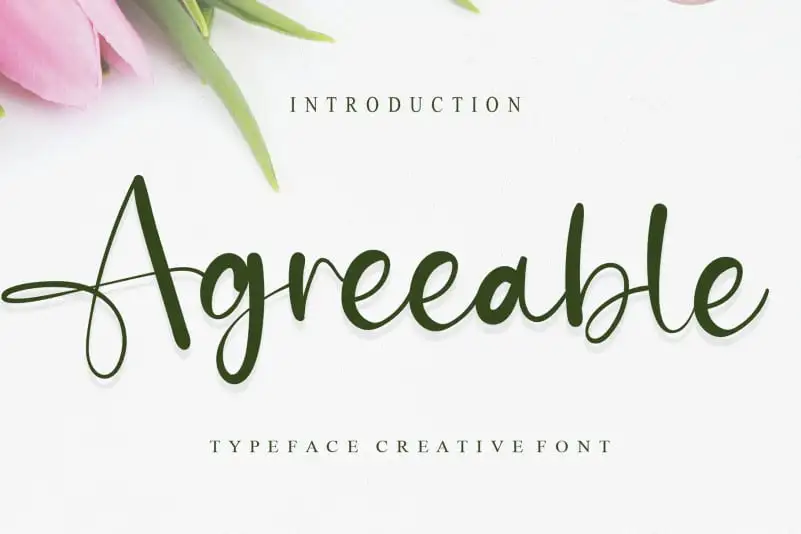
Agreeable Calligraphy Font – Download Grátis
Descubra uma nova experiência com a Fonte Script ‘Agreeable Calligraphy’. Inspirada no universo natural brasileiro vibrante e diversificado, esta fonte traz uma sensação de caligrafia delicada e sofisticada. Seu designer, andikastudio, criou este recurso especial para oferecer aos seus usuários um produto excepcionalmente original que reflete a riqueza cultural do Brasil. Através deste script fonte, você pode capturar o jeito quase mágico como as folhas de árvores dançam ao vento em meio à paisagem verde e acolhedora da nossa Amazônia. Ou, se preferir, a caligrafia mais suave do sertão nordestino, onde o ar é densoado pela força das tempestades que chegam das águas do Atlântico. Essa fonte não apenas oferece uma maneira única de expressar palavras e ideias, mas também oferece um convite a explorar os mais diversos aspectos da cultura brasileira. Ela é perfeita para designers gráficos que valorizam cada detalhe natural, desde as formas arredondadas do papel no momento da impressão até o espírito inspirador presente em cada letra. Engane-se e deixe a natureza inspirar sua criação com a Fonte Script ‘Agreeable Calligraphy’.